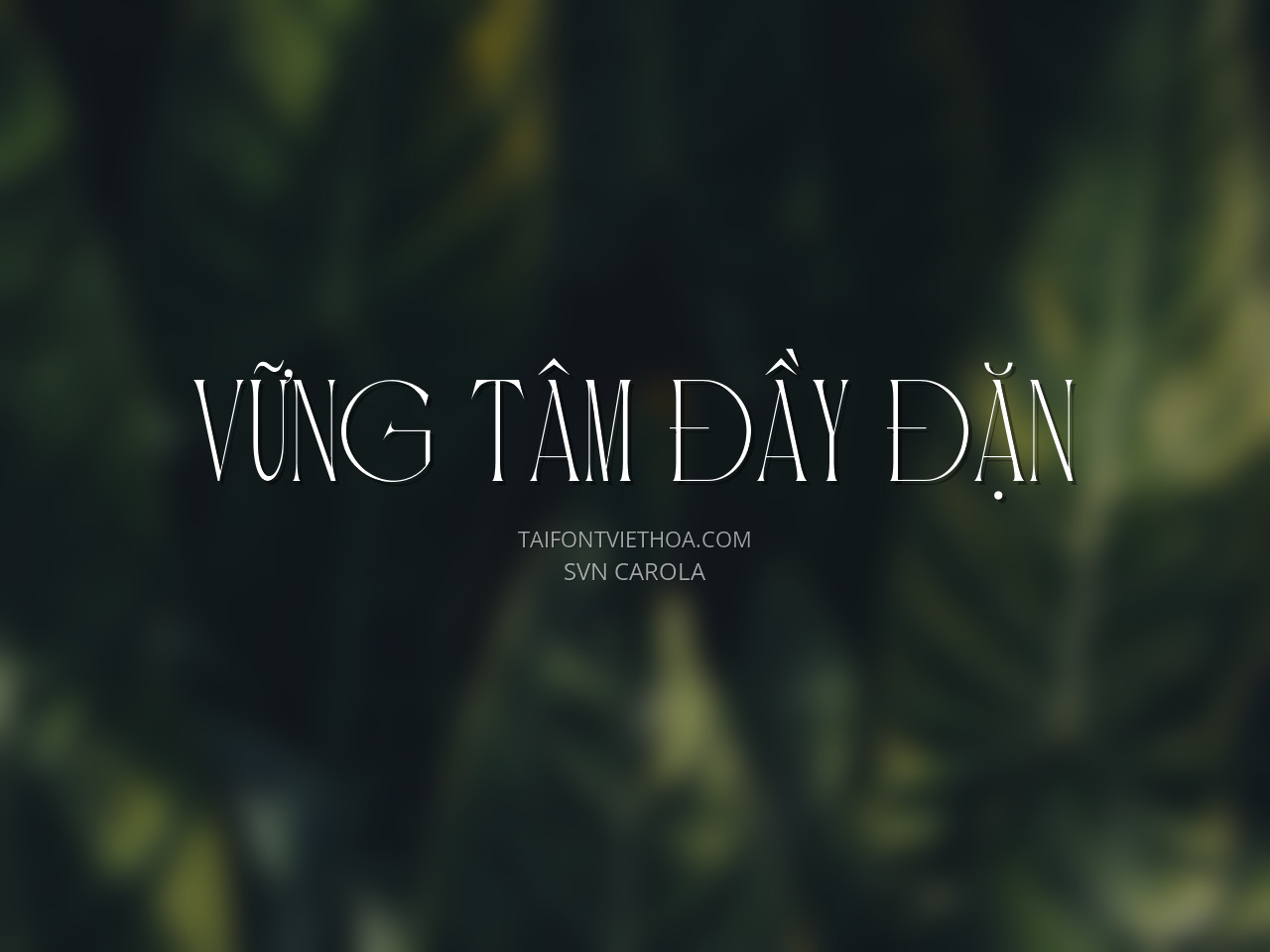
Font việt hóa SVN Calora
Giới thiệu về font SVN Calora – Kiểu chữ serif thanh lịch, hiện đại và mềm mại
SVN Calora là phiên bản Việt hóa của font Calora – một kiểu chữ serif mang phong cách thanh lịch, hiện đại và mềm mại. Font được thiết kế với các nét chữ cân đối, tinh tế và có độ tương phản nhẹ nhàng, rất phù hợp cho các dự án thiết kế thương hiệu, in ấn và truyền thông cao cấp.
Phiên bản Việt hóa của SVN Calora đã được Taifontviethoa.comchăm sóc kỹ lưỡng, hỗ trợ đầy đủ dấu tiếng Việt cùng hơn 80 ngôn ngữ khác. Font giúp các nhà thiết kế dễ dàng áp dụng trong nhiều sản phẩm đa dạng mà vẫn giữ được vẻ đẹp tinh tế và chuyên nghiệp.
Thiết kế serif mềm mại – Ứng dụng rộng rãi trong thương hiệu và xuất bản
SVN Calora sở hữu cấu trúc serif với các nét chữ mềm mại, uyển chuyển và hài hòa. Font phù hợp cho đoạn văn bản dài và tiêu đề, giúp tăng tính thẩm mỹ và sự chuyên nghiệp cho thiết kế. Phong cách của Calora mang đến sự thanh lịch và sang trọng cho mọi sản phẩm thiết kế.
Ứng dụng lý tưởng: thiết kế nhận diện thương hiệu, bìa sách, tạp chí, brochure, thư mời, danh thiếp và các ấn phẩm quảng cáo cao cấp. Ngành nghề phù hợp: thời trang, mỹ phẩm, nội thất, giáo dục, xuất bản và các thương hiệu định vị theo phong cách thanh lịch, hiện đại.